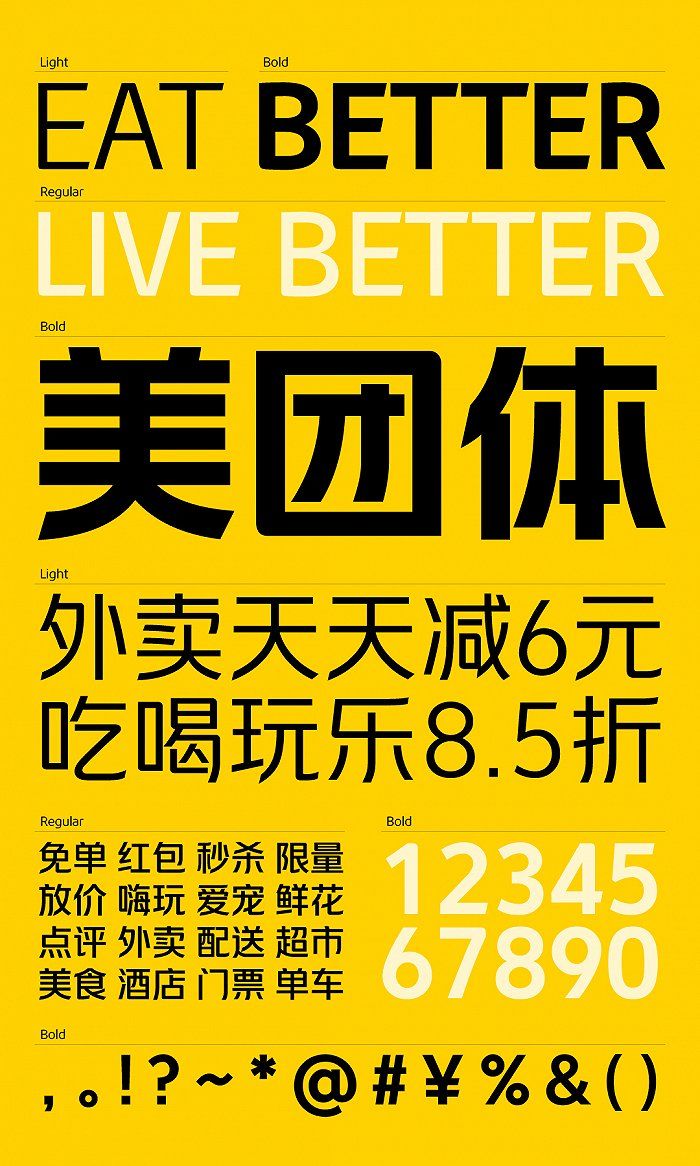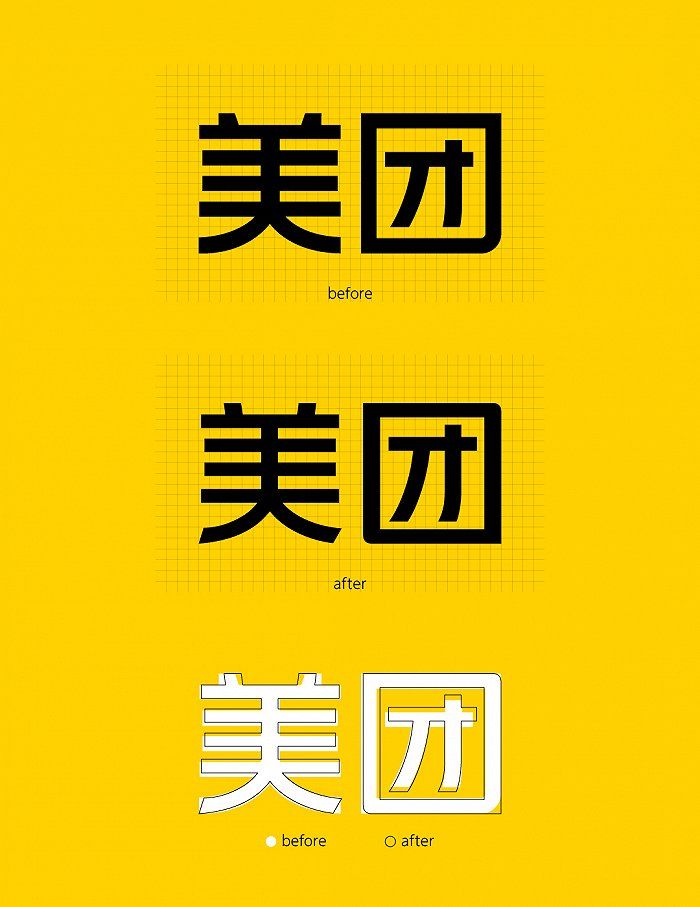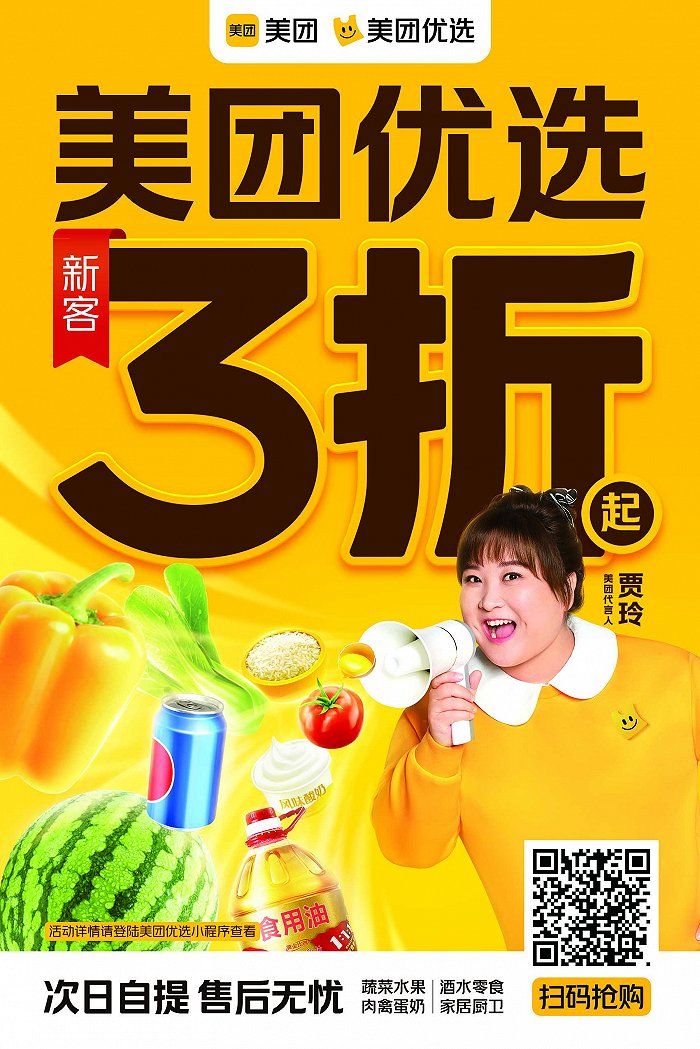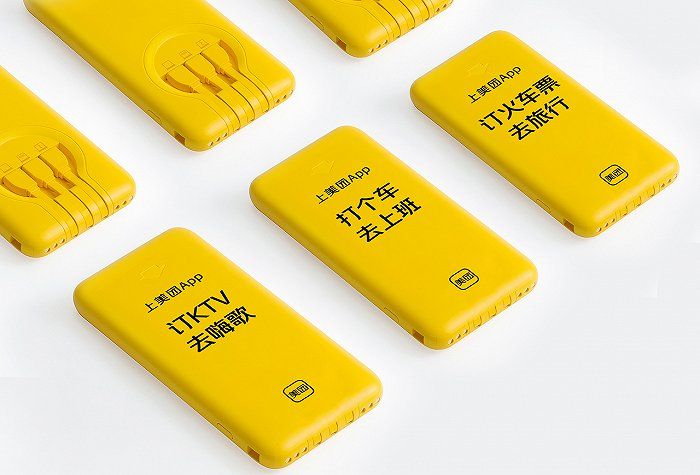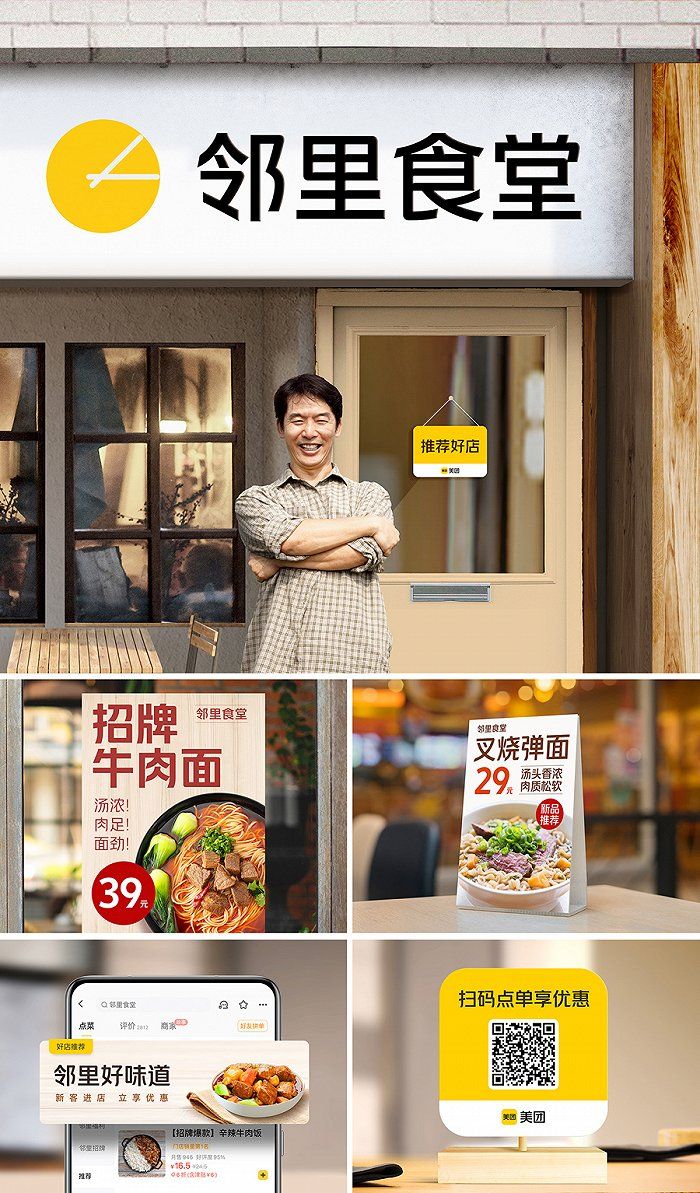
字体作为品牌的可视化呈现,是品牌体验中的重要一环,继品牌色“美团黄”的推出后,近日,由方正字库团队主导设计的美团全新定制字体——“美团体”正式发布。
伴随美团品牌场景的日益丰富,需要适配并统一线上+线下的各类应用场景,打造更细致入微的服务体验。如何在保证字体的艺术美感和规范性的同时,恰当地运用文字形态来表现企业文化和品牌调性;如何在每个品牌场景的接触点上,都能以最合理、最清晰的视觉形象,来满足用户对美团品牌的心智感知,都成为新字体设计开发中遇到的巨大挑战。
方正字库以原有 LOGO 为出发点,在融会美团企业文化和品牌形象的基础上,通过对笔形笔画、字体部件、字面空间的再设计,构建出全新的品牌字体规范。美团体部分撇捺采取斜切方式,赋予字形向前奔跑的姿态和势能。
作为人们生活服务的小帮手,美团希望给人们传递温暖、亲近的感受,美团体在设计上试图还原这样一份亲和与圆融:四方笔画结构采取左下、右上双角倒圆处理,让字形方圆有致,刚柔并济,传递生活的温度。此外,高重心线的设计方式,使字体呈现出轻盈向上的挺拔姿态。
美团体共包含Light、Regular、Bold三个字重, 西文设计沿袭了汉字斜切+圆角的主要笔画特征,与中文搭配使用时具有一致的视觉识别性。
经过方正字库和美团品牌团队的共同推敲、反复打磨,最终呈现融合了前进的速度、亲和的温度以及年轻的态度的美团体,双方的通力协作,将美团全力奔赴未来、,追求更好的目标与使命融入字体的一笔一画当中,写下属于这个时代的表达。
未来,美团体将广泛应用于覆盖美团品牌线上+线下的各类美团品牌应用场景中,还将通过授权美团合作商户免费使用,帮助美团合作商户自主使用字体,进行线上线下店铺视觉优化。在今后的日子里,“美团体”将在赋能业务的同时,帮助企业书写社会责任,依托自身平台优势和丰富的生活服务场景,致力于在整个生态系统中共享社会责任理念,透过字体为用户、行业和社会创造更多价值和美好。